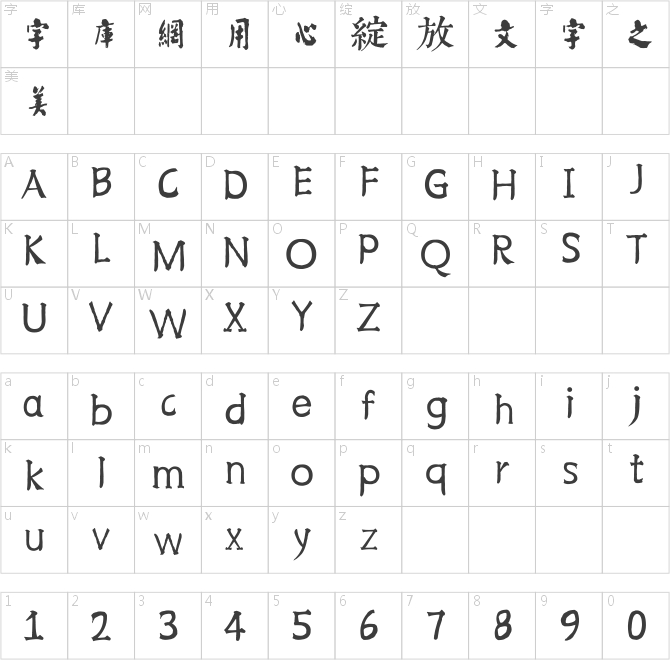
邯鄲朱熹榜書千字文字體下載邯鄲(宋)朱熹榜書千字文
注:本字庫為古籍千字文復刻書法小字庫,字符數(shù)量為1000余字,如有特殊需求,可以聯(lián)系邯鄲字庫韓紹杰為您訂制,也可以聯(lián)系本站客服為您轉答!朱熹(1130年10月18日-1200年4月23日),字元晦,又字仲晦,號晦庵,晚稱晦翁,謚文,世稱朱文公。祖籍徽州府婺源縣(今江西省婺源),出生于南劍州尤溪(今屬福建省尤溪縣)。宋朝著名的理學家、思想家、哲學家、教育家、詩人,閩學派的代表人物,儒學集大成者,世尊稱為朱子。朱熹是唯一非孔子親傳弟子而享祀孔廟,位列大成殿十二哲者中,受儒教祭祀。 [1] 朱熹是“二程”(程顥、程頤)的三傳弟子李侗的學生,與二程合稱“程朱學派”。朱熹的理學思想對元、明、清三朝影響很大,成為三朝的官方哲學,是中國教育史上繼孔子后的又一人。 朱熹十九歲考中進士,曾任江西南康、福建漳州知府、浙東巡撫,做官清正有為,振舉書院建設。官拜煥章閣侍制兼侍講,為宋寧宗皇帝講學。 朱熹著述甚多,有《四書章句集注》《太極圖說解》《通書解說》《周易讀本》《楚辭集注》,后人輯有《朱子大全》《朱子集語象》等。其中《四書章句集注》成為欽定的教科書和科舉考試的標準。
邯鄲朱熹榜書千字文字體邯鄲(宋)朱熹榜書千字文字庫是一款讓人賞心悅目、百看不厭的中文字體,適合各類廣告和產(chǎn)品包裝設計應用,字體大小7.34MB,格式為ttf字體,上傳用戶是邯鄲字庫,作者/版權方為韓紹杰